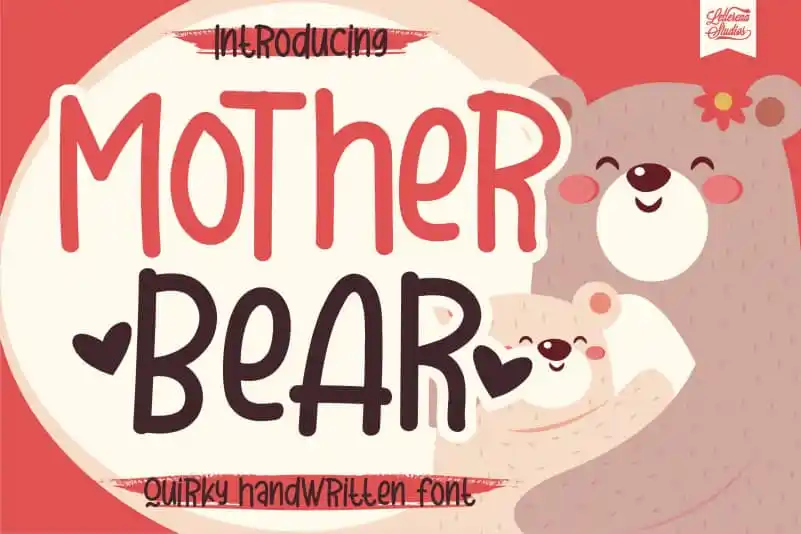
Mother Bear Display Font – Fonte Grátis
Mother Bear Display Font
A Mother Bear Display Font é uma fonte manuscrita irônica com estilo amigável perfeita para quem busca adicionar um toque peculiar aos projetos DIY. Esta fonte é ideal para personalizar artefatos caseiros e objetos de decoração, tornando seus trabalhos únicos e imprimindo uma sensação de hospitalidade genuína em cada peça criada. A Mother Bear Display Font é a escolha perfeita para quem busca um charme descontraído e versátil sem perder a personalização que tanto valorizamos na nossa arte handmade. Sempre que você usar esta fonte, seu projeto ganhará vida através de uma pitada de originalidade única.